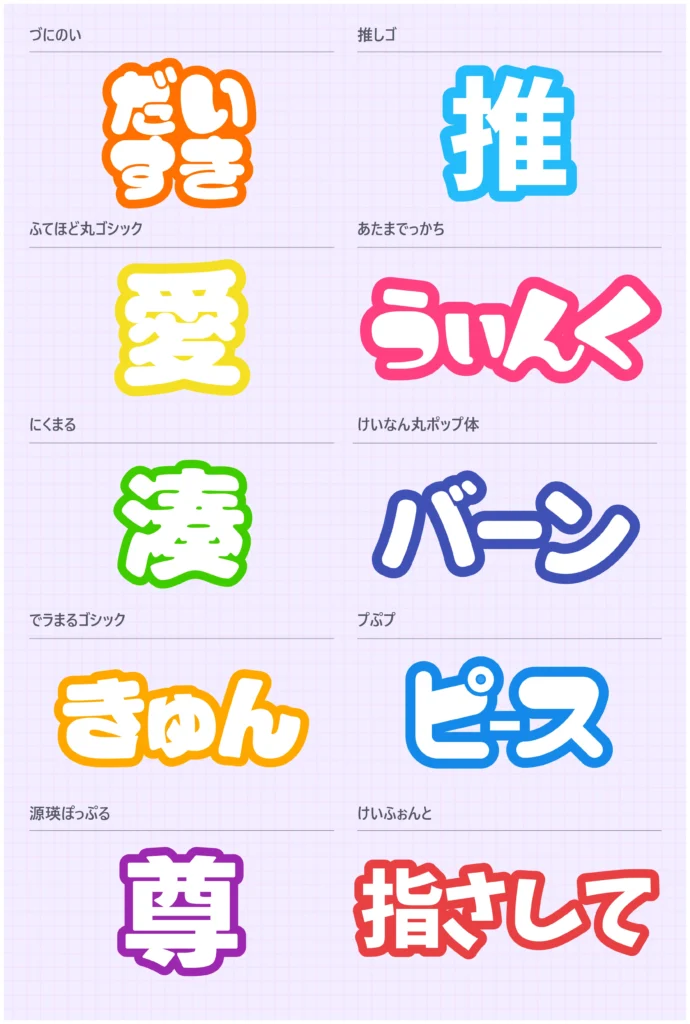
ライブやイベント会場で映えるよう、太めで丸みを帯びたラインが特徴の「うちわ文字」向けフリーフォントは、アイドル応援や推し活グッズ作りなど、ポップで楽しい雰囲気を演出したい場面にぴったりです。
うちわ文字のフォント
今回ご紹介するのは、無料で使えて商用利用も可能なかわいいフォントたち。遠くからでもしっかり視認できる太字デザインや、コロンとした丸みが愛らしい文字、立体感のあるポップな書体、手描き風の温かみを感じるデザインなど、うちわ文字ならではの“目立つ可愛さ”を引き出せるタイプを厳選しました。
「推しに気づいてもらえるうちわを作りたい」「他のファンと被らないデザインにしたい」――そそんな想いを形にする、フォント探しの参考にしてみてください。
1.推しゴ
推しゴ
視認性★★★★★
目立ち度★★★★★
力強い極太ゴシック体で、存在感は抜群。シンプルながらも直線的な形状がくっきり映え、派手な縁や濃い背景色とも相性抜群。ライブやイベント会場でも一瞬で目を引きます。
2. デラまるゴシック
デラまるゴシック
視認性★★★★★
目立ち度★★★★★
極太で安定感のあるゴシック体。太い線幅が遠距離からでもくっきり見え、明るい縁取りや派手な配色にも負けません。汎用性が高く、どんな場面でも安心して使えます。
3. ふてほど丸ゴシック
ふてほど丸ゴシック
視認性★★★★★
目立ち度★★★★★
均整の取れた太めの丸ゴシック体で、柔らかい印象と高い視認性を両立。色や装飾の自由度が高く、明るい縁取りや濃い背景でも文字がしっかり際立ちます。汎用性の高さも魅力。
4. 源暎ぽっぷる
源暎ぽっぷる
視認性★★★★★
目立ち度★★★★☆
太くて丸みのあるポップなデザインが特徴。明るい色と組み合わせると視認性がさらに高まり、ライブやイベントでの存在感も抜群です。
5. Mike(づにのい)
づにのい
視認性★★★★☆
目立ち度★★★★☆
極太で丸みのあるフォルムが特徴的。やさしい印象を持ちながらも迫力があり、推しの名前やメッセージを大きく際立たせます。派手な縁取りや明るい背景にも負けず、遠くからでも視認性抜群です。
6. にくまる
にくまる
視認性★★★★☆
目立ち度★★★★☆
コロンとした丸みとしっかりした太さが特徴で、可愛いのに読みやすいバランス設計。背景や縁色を変えるだけで印象がガラッと変わるため、幅広いアレンジが可能です。
7. けいふぉんと!
けいふぉんと!
視認性★★★★★
目立ち度★★★★★
程よい太さと丸みがバランス良く、長時間見ても疲れにくい読みやすさが魅力。背景や縁色を選ばず、多様なデザインに対応できる万能フォントです。
8. けいなん丸ポップ体
けいなん丸ポップ体
視認性★★★★★
目立ち度★★★★☆
ポップで親しみやすい雰囲気の丸ゴシック体。縁取りや明るい配色と組み合わせればさらに可愛さが引き立ち、応援うちわやイベントボードにもぴったり。
9. プぷプ
プぷプ
視認性★★★★☆
目立ち度★★★★☆
やわらかな曲線と遊び心のあるデザインが魅力。可愛らしさと独自性を兼ね備え、他のうちわ文字と差をつけたいときにおすすめです。
10. あたまでっかち
あたまでっかち
視認性★★★☆☆
目立ち度★★★☆☆
上部が大きめにデザインされた個性的なフォルムが特徴。可愛らしさとインパクトを兼ね備えており、近距離でのうちわやメッセージボードで個性を出したいときに最適です。